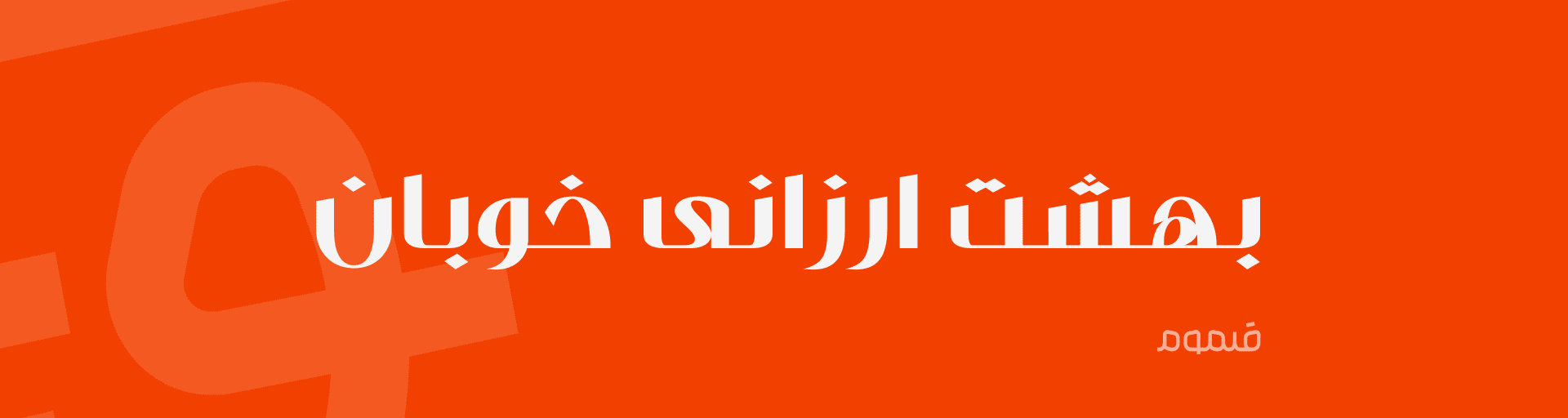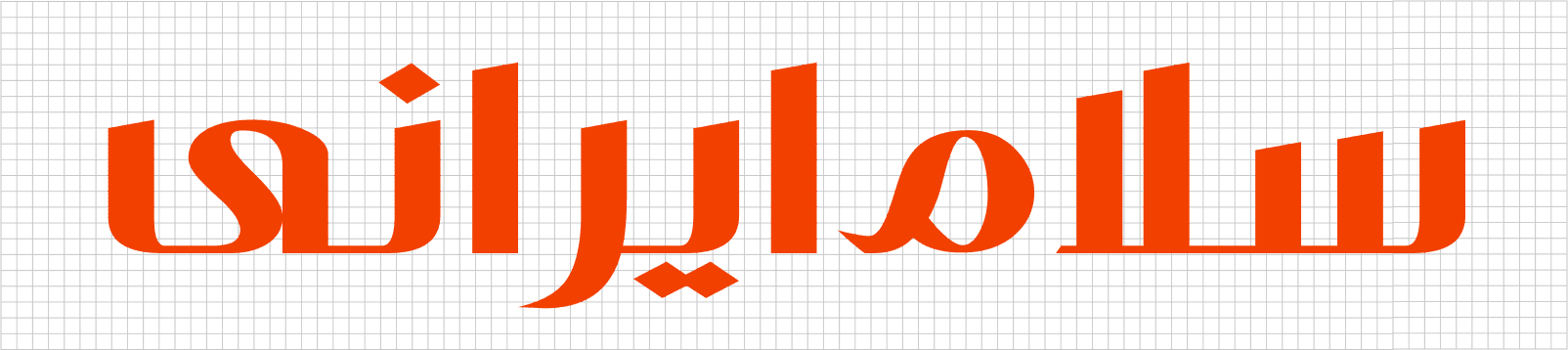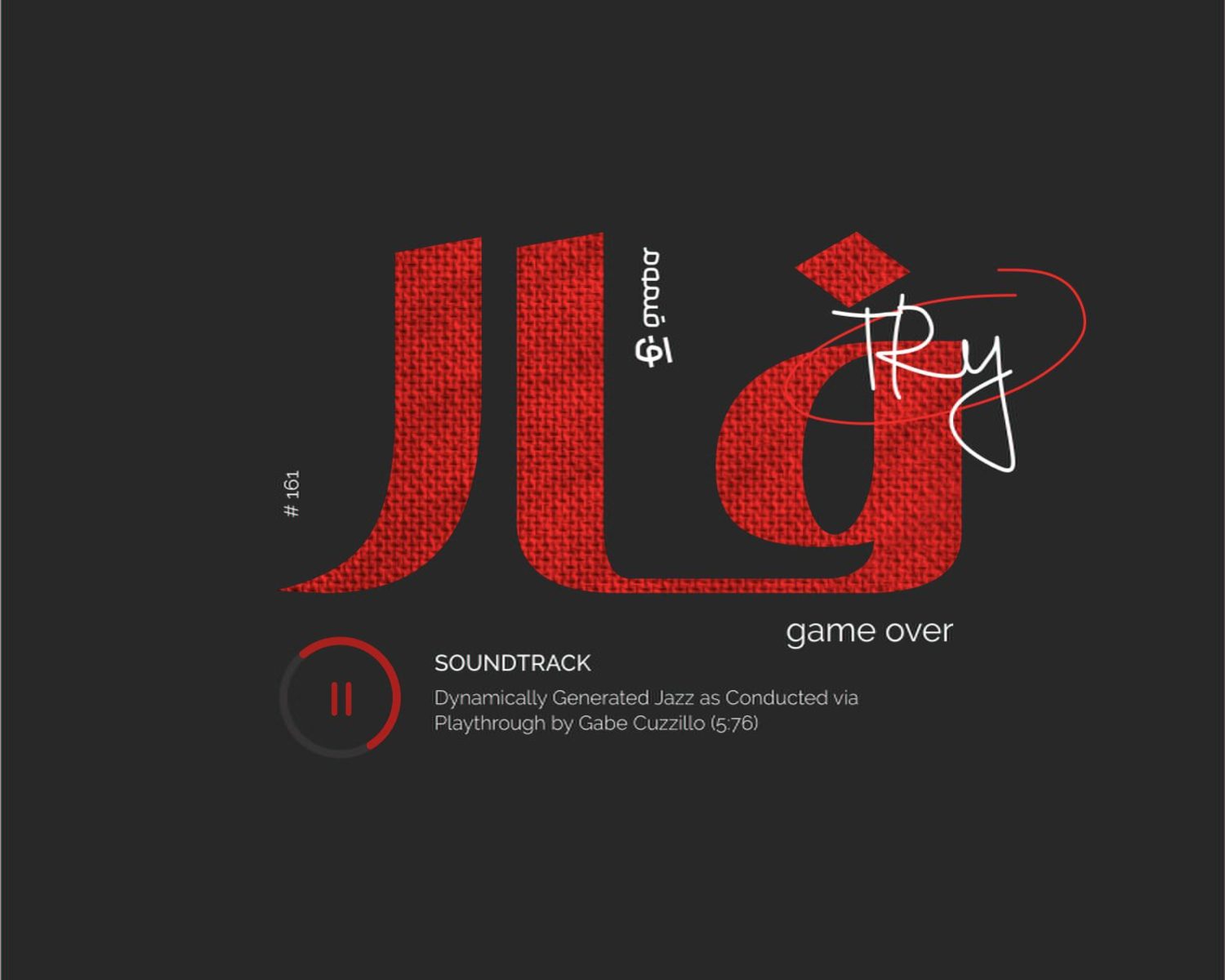
فونت فارسی فار یک فونت هندسی است که میتواند در طراحی لوگوتایپ و همچنین نوشتن تیتر ها به شما کمک کند. این فونت را به صورت رایگان دانلود کنید
فونت فارسی فار
حروف در فونت فارسی فار، دارای ساختاری شکننده و بدور از انتظار میباشند. به همین دلیل مخاطب را مجذوب خود کرده و حس کنجکاوی را در بیننده بوجود می‌آورد.
کاربرد این فونت بیشتر در نوشتن عنوان مطالب شماست. مطمئن شوید که از این فونت در متن های طولانی استفاده نکنید! استفاده این فونت در متن های بلند باعث خستگی چشم شده و به هیچ وجه توصیه نمیشود.
فونت فارسی فار